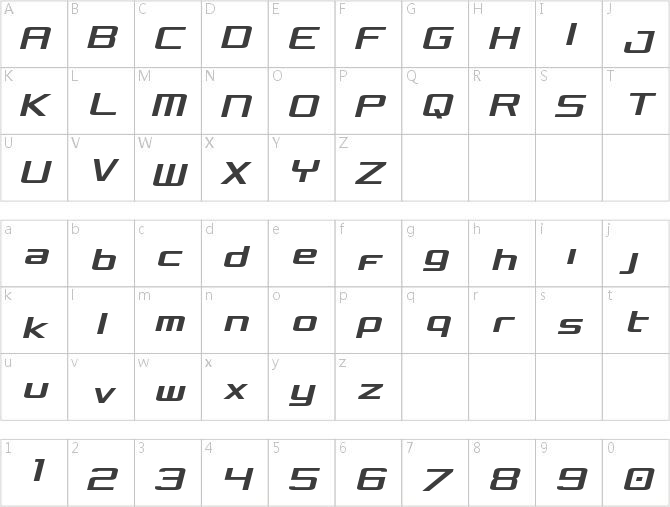
字體名稱: conciel
concieliancondsemital
concieliancondsemital介紹
concieliancondsemital字體字庫是一款讓人賞心悅目、百看不厭的英文字體,適合各類廣告和產品包裝設計應用,字體大小0.03MB,格式為ttf字體,上傳用戶是KISEKI,作者/版權方為未知